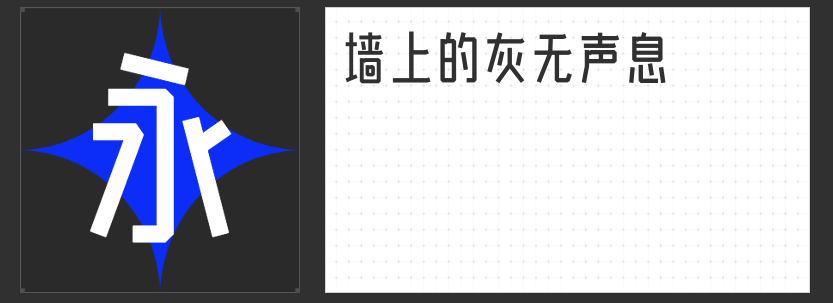
正文排版新选择:四款高效实用字体推荐
在设计与排版的世界里,正文字体的选择往往决定了阅读体验的质量。一款优秀的正文字体,需兼顾易读性、美观性与风格适配性。以下四款字体,以其独特的设计语言,为正文排版提供了多样而精致的解决方案。
一、高手庆科竞速体 常规
此字体以瘦长工整著称,布白均匀,中宫紧凑,确保在密集排版中仍能保持良好的阅读流畅性。其直线设计使得横竖笔画视觉等粗,减少了视觉疲劳;独特的“去钩后笔画末端往内部加斜”处理,既保持了字体的简洁工整,又增添了设计的巧思。适合科技类文档、报告等需要高效阅读的场景。
二、 励字美黑简
融合黑体的力量感与宋体的优雅线条,励字美黑简展现出匀称清秀的美学特质。它摒弃了黑体可能带来的生硬,又保留了宋体的文化底蕴,给人以端正而富有活力的视觉印象。适用于企业文化手册、教育材料等需兼顾正式与亲和力的正文。
三、励字魔方黑简
这款字体以方正简洁为核心,横竖笔形粗细对比鲜明,方头方尾的设计语言直接而有力。无装饰的风格使其在各种媒介上都能保持高辨识度,非常适合需要强调信息、吸引眼球的标题或重点段落。在数字阅读与印刷品中,都能展现出色。
四、 励字玉树临风简
以其瘦长端正的身姿,励字玉树临风简散发出一种拙中见巧的质朴美感。字形修长而不失稳重,风格朴实敛静,却在细节处透露出设计的匠心。无论是广告设计、书籍正文还是品牌宣传,它都能为作品增添一份独特的文化韵味。
这四款字体,从现代极简到传统韵味,从高效阅读到情感传递,各有千秋。高手庆科竞速体以秩序感见长,励字美黑简融合经典与创新,励字魔方黑简以醒目著称,励字玉树临风简则传递着质朴的美学。它们不仅是工具,更是设计语言的延伸,助力每一次正文排版都能精准传达信息,触动人心。